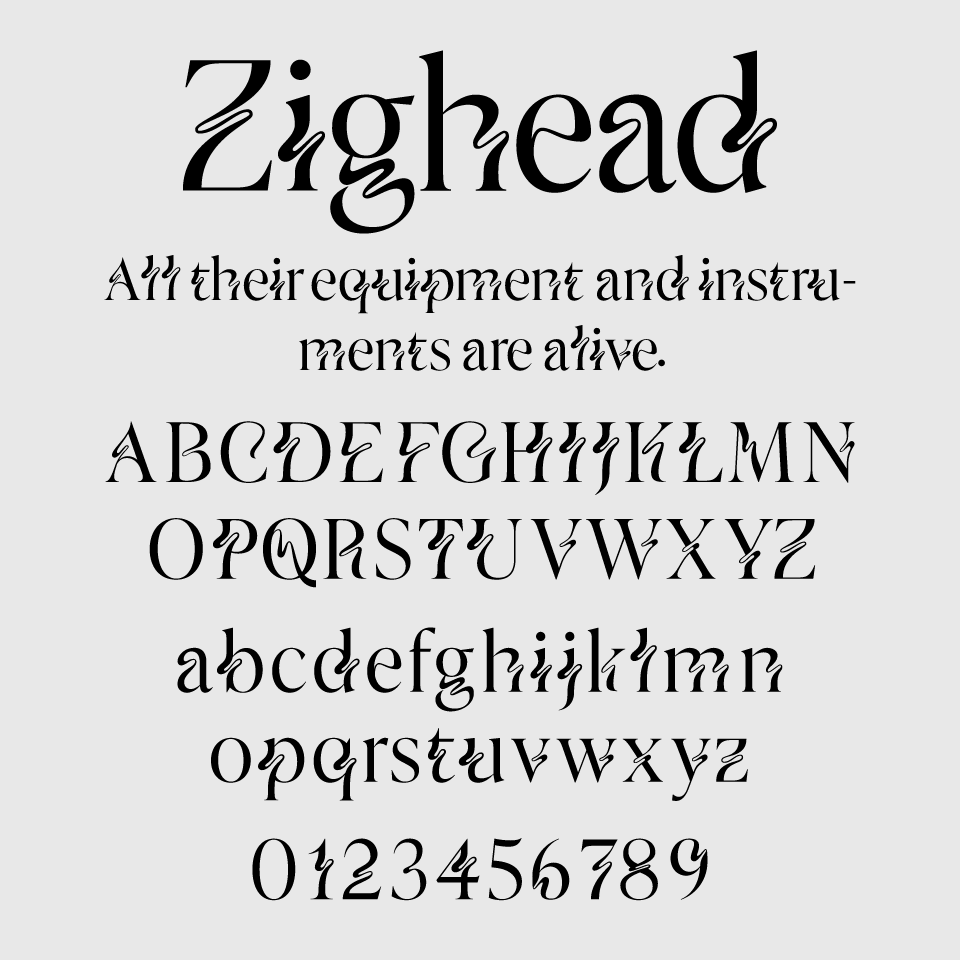
Zigheadフォントは、手書きのような不規則さと、うねるようなラインが混ざり合った、まるで踊っているかのようなフォントです。
一文字ごとに個性があり、水の波紋のような流れるようなリズム感が魅力なデザインです。
ちょっとミステリアスで、でも愛嬌もあって。サーカスの看板や、音楽フェスのタイトルなど、自由なテンションを伝えたいときに使いたくなるような、クセになるフォントです。